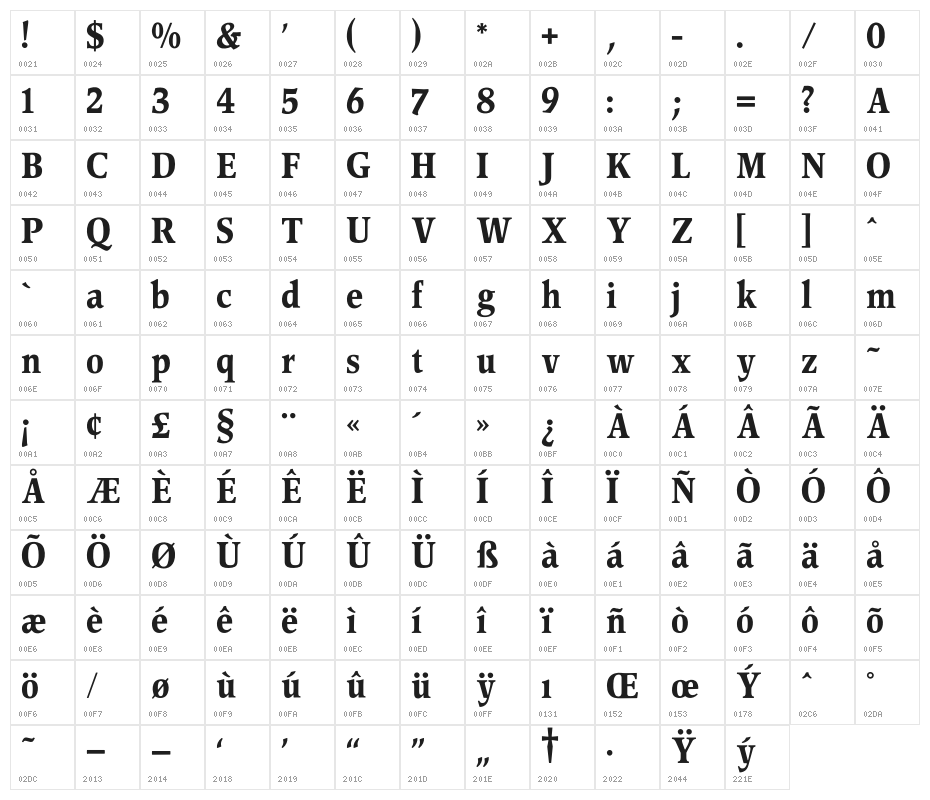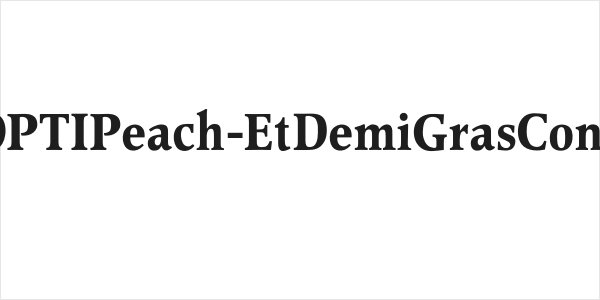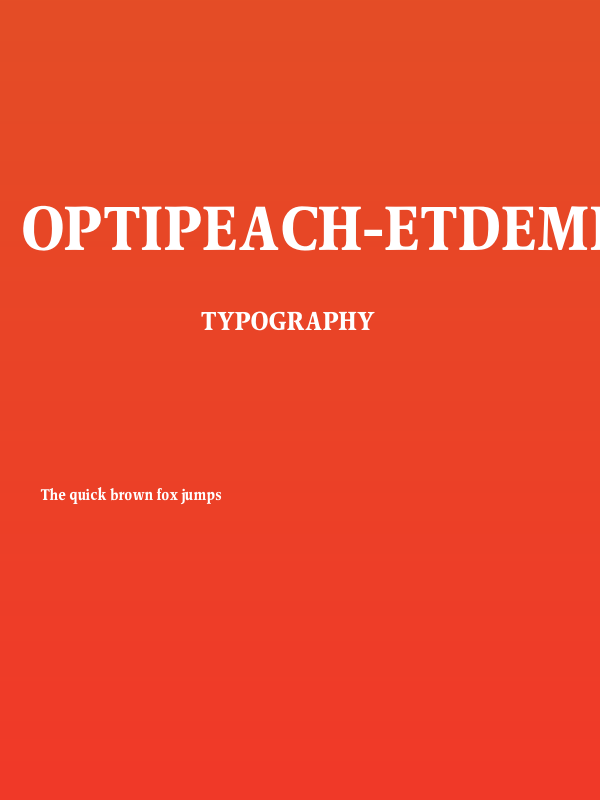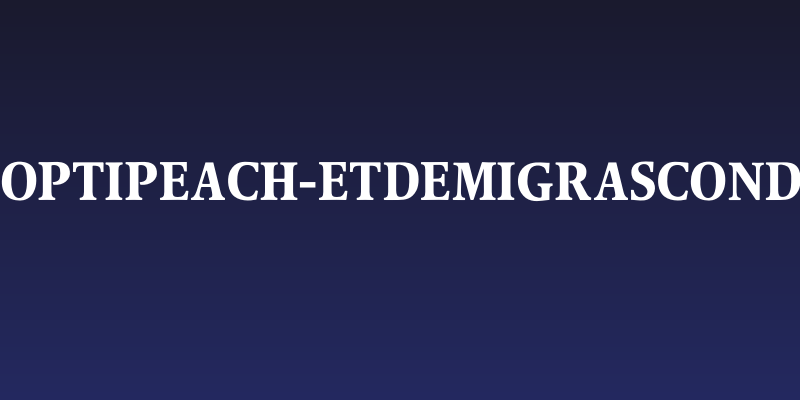
OPTIPeach-EtDemiGrasCond Font
| Gesamtstil | Classic |
| Vorgeschlagene Projekte | Ideal for headlines, posters, branding, and editorial design where a strong, classic presence is desired. |